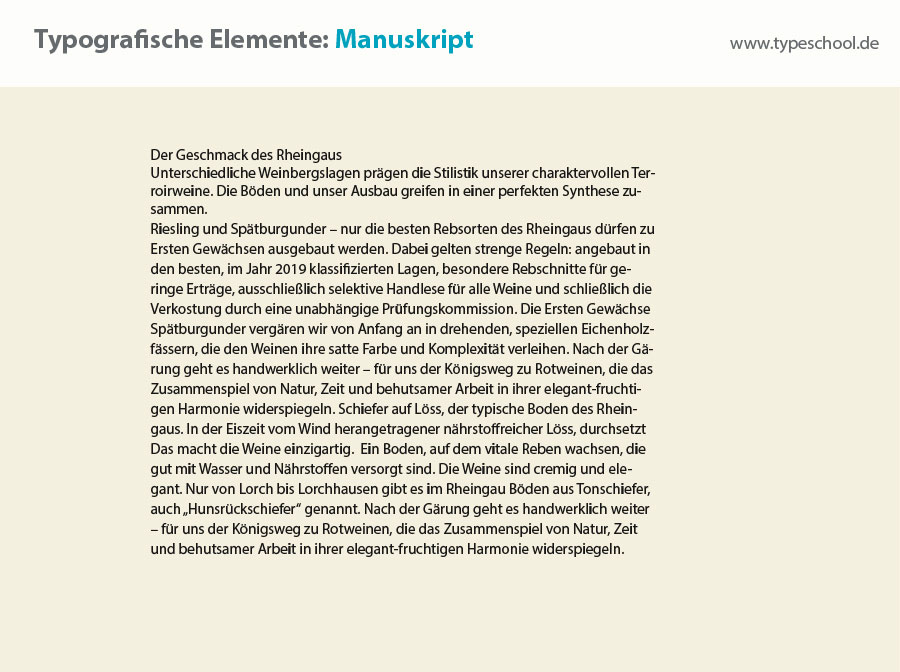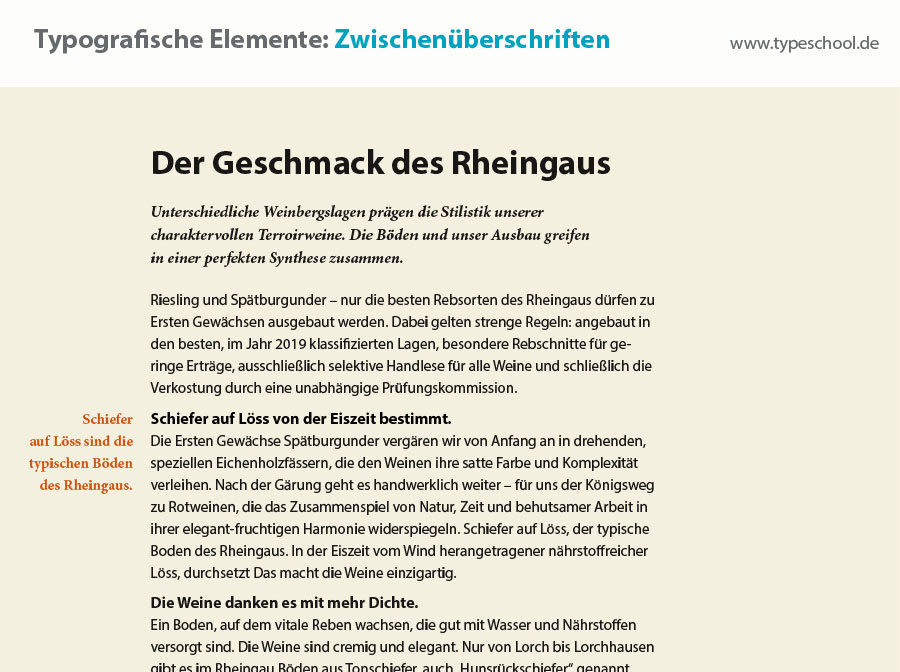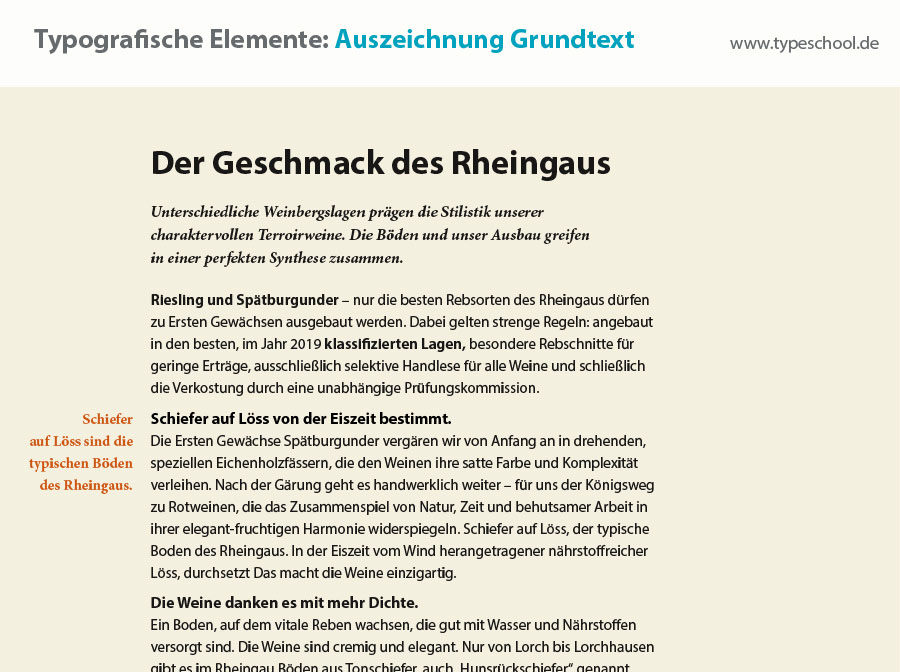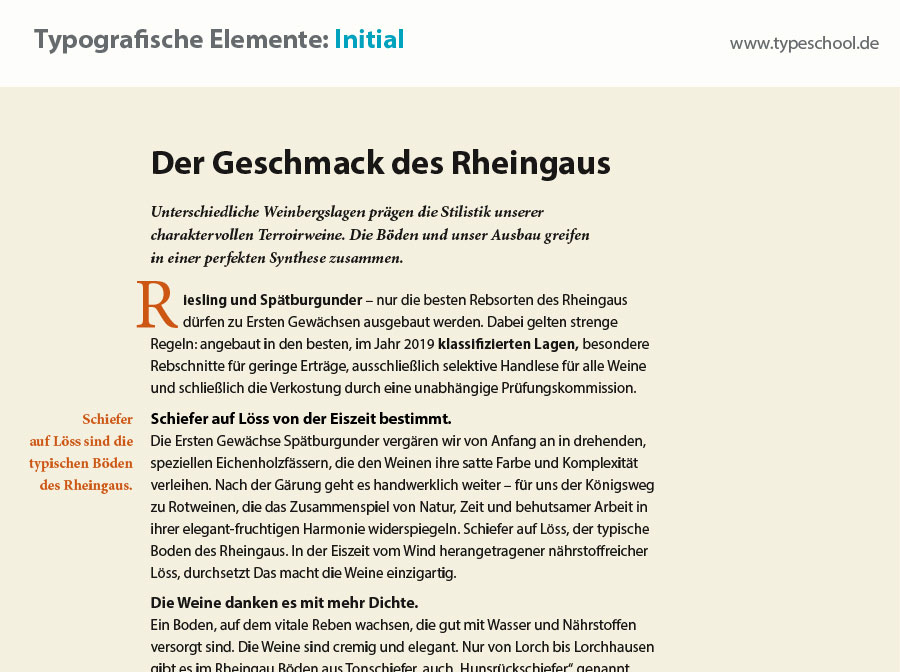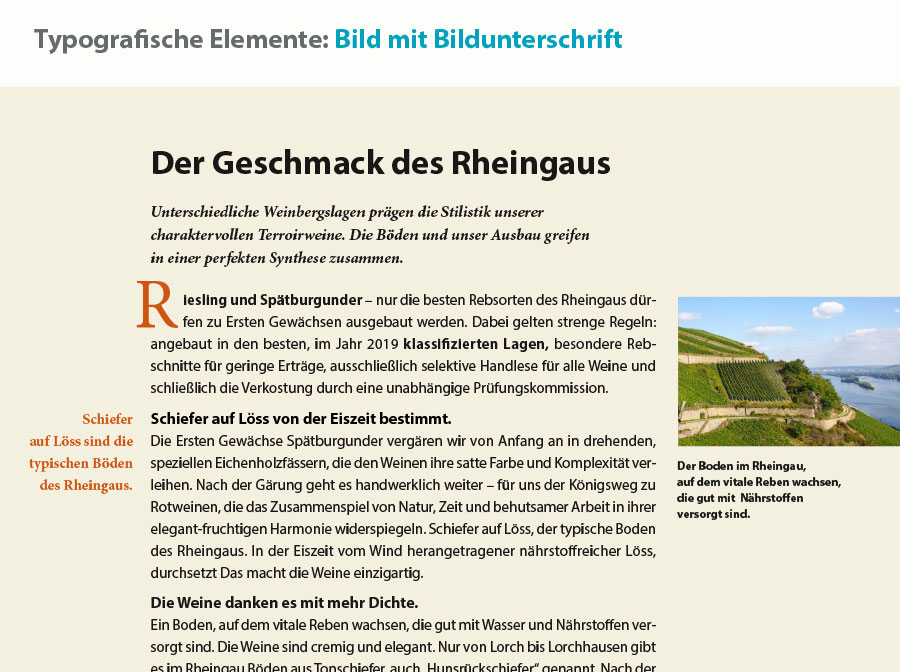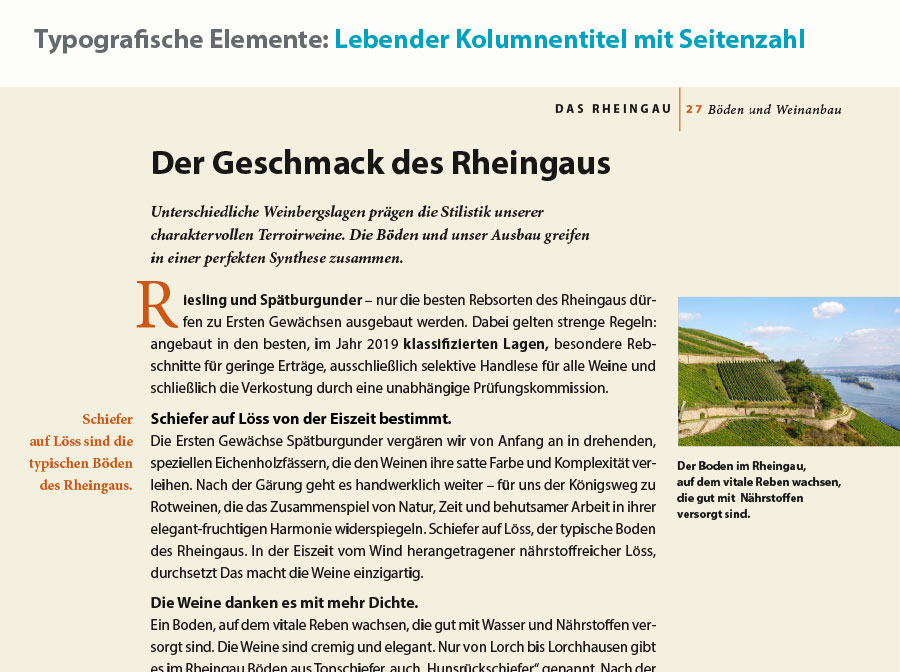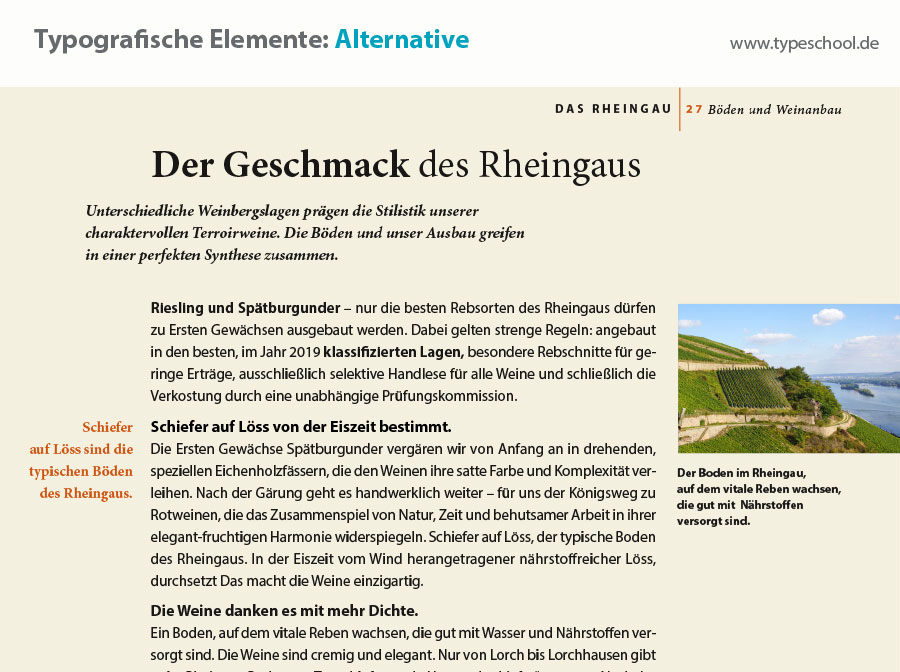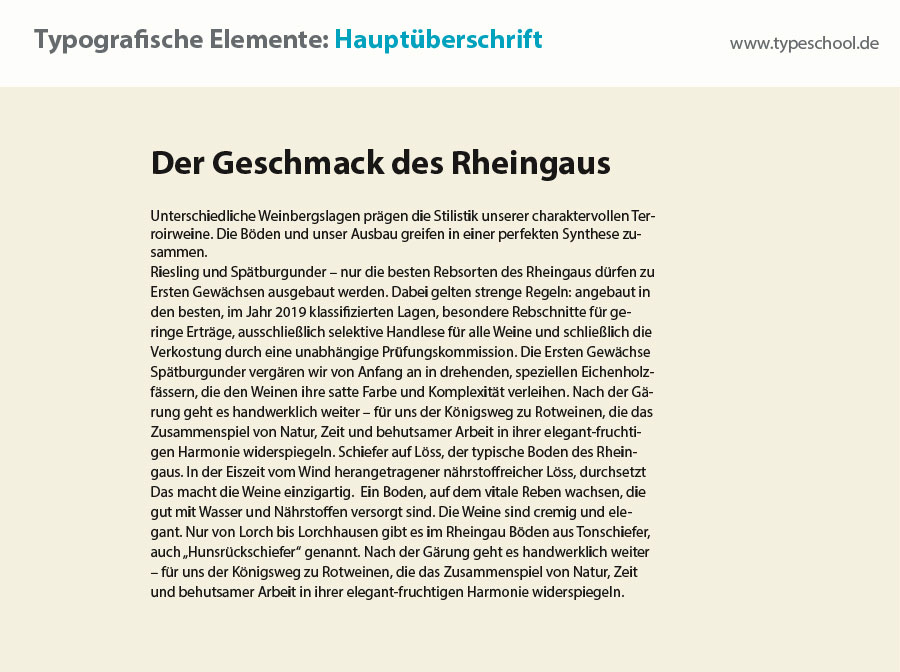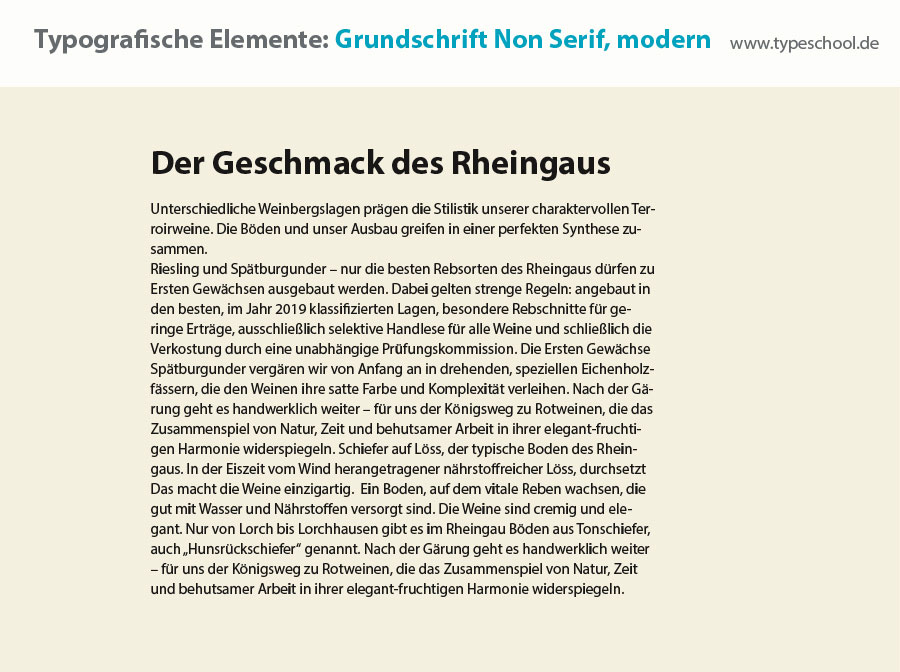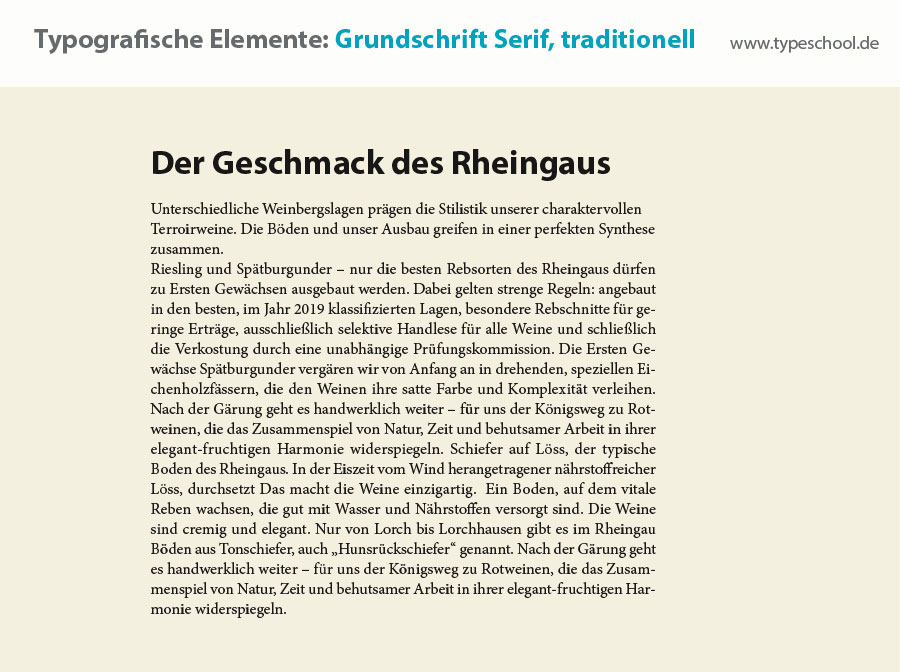
Makro- und Mikrotypografie: mit den wichtigsten typografischen Elementen strukturiert visualisieren – eine Übersicht.
Befragt man Google, was genau man unter Typografie versteht, so erhält man unzählige Antworten und Meinungen. Wikipedia zumindest antwortet eher nüchtern aber sachlich: „Heute bezeichnet Typografie meist den medienunabhängigen Gestaltungsprozess, der mittels Schrift, Bildern, Linien, Flächen und Leerräumen alle Arten von Kommunikationsmedien gestaltet.“ Und weiter: „Mithilfe von Typografie können der Inhalt, der Zweck oder die Anmutung einer Information verdeutlicht werden.“ Quelle: Wikipedia, Typografie.
Typografie ist keine Kunst
Entgegen der Meinung, Typografie sei eine Kunst, die sich auf schöne Schriften, Laufweiten der Schrift oder genauen Zeilenabständen beschränke, halte ich es mehr mit dem Zitat von Günter Gerhard Lange, der einmal sagte: „Typografie übersetzt eine Information in eine Botschaft.“
Ich möchte sogar noch einen Schritt weitergehen: Typografie umfasst visuelle Elemente, mit denen Produkt- oder Dienstleistungsmerkmale transparenter und aufmerksamkeitsstärker dargestellt werden können.
Typografie ist also keine Kunst, sondern einfach gesagt ein Teil der Informations- und Verkaufsförderung. So habe ich es als Typograf, Designer und Inhaber einer Werbeagentur jahrzehntelang gesehen und praktiziert – mit Erfolg!
Typografische Elemente strukturieren Informationen
Was macht Typografie so spannend? Bereits die Auswahl geeigneter Fonts ist der erste wichtige Einstieg in ein neues Projekt – kann man doch damit am besten den Look & Feel eines Designs bestimmen. Auch für einen erfahrenen Designer ist das Thema Schriftauswahl und Schriftmischung immer auch der schwierigste Part im Designbereich. In einem früheren Blogbeitrag habe ich dazu eine Empfehlung gegeben, die Einsteigern und weniger erfahrenen Gestaltern eine Hilfestellung bei der Auswahl von Fonts geben kann.
An dieser Stelle möchte ich Ihnen eine Übersicht geben, welche wichtigen Elemente wir in der Makro- und Mikrotypografie kennen, mit denen wir in Kombination den sogenannten typografischen Spannungsbogen im Layout erzeugen und sich Informationen strukturierter und betonter visualisieren lassen.
Hier ein Ablauf der einfachsten typografischen Elemente, mit denen ich am häufigsten Informationen typografisch strukturiere.
Hauptüberschrift
Die Hauptüberschrift ist der direkte Einstieg ins Thema. Sie strukturiert die Kommunikation und übernimmt auch eine ästhetische Funktion. Die Hauptüberschrift beeinflußt das typografische Klima einer Kommunikation und bestimmt durch die passende Wahl eines Fonts sehr deutlich den Look & Feel eines Designs. Die Hauptüberschrift soll nicht nur informieren, sondern vor allem eine Botschaft transportieren. Gestalterisch hebt sie sich in Schriftgröße und Auswahl der Schrift deutlich vom Grundtext ab.
Grundschrift
Bei der Grundschrift ist die Auswahl der Schriftart sowie die Schriftgröße und der Zeilenabstand besonders wichtig.
Legen Sie fest, ob der Look & Feel eines Designs eher von einer Schrift mit Serifen (Serif Font) oder einer serifenlosen Schrift (Non Serif Font) bestimmt werden soll.
Eine serifenlose Schrift verkörpert eher das Moderne, eine Schrift mit Serifen eher ein gediegenes und traditionelles Design.
Bei Verwendung einer serifenlosen Grundschrift sind Schriftgrößen zwischen 8 und 9 Punkt grundsätzlich geeignet. Eine Grundschrift mit Serifen darf eher einen Punkt größer sein.
Als Zeilenabstand empfehle ich eine Größe von 140 % der Schriftgröße. Ein Beispiel: Beim »Non Serif Font“ Myriad Pro 9 pt wäre für den Lesetext ein Zeilenabstand von 13 pt gut gewählt. Das entspricht auch der heutigen Lesegewohnheit, die durch das Lesen von Texten auf mobilen Endgeräten bestimmt wird. Bei „Serif Fonts“ geben Sie ruhig noch 1 pt dazu.
Bestimmt werden Schriftgröße und Zeilenabstand natürlich von der Schriftart, der Textmenge und der Zeilenlänge – daher vergleichend ausprobieren.
Textvorspann
Der Textvorspann ist ein Bindeglied zwischen Headline und Lesetext. Er soll die erste Aufmerksamkeit aufgreifen und „weiterreichen.“ Im Textvorspann soll inhaltlich alles kommuniziert werden, was der Grundtext vertieft. Gestalterisch soll er sich – wie das Beispiel zeigt –, deutlich in Schriftart, Schriftauszeichnung, Schriftgröße, Zeilenlänge, Zeilenabstand und Satzart von der Hauptüberschrift und dem Grundtext unterscheiden.
Marginaltext
Marginalien sind Randbemerkungen, die zusätzliche Informationen oder weitergehende Erklärungen zum Grundtext bieten. Marginalien sind seit dem Mittelalter als handgeschriebene Randspaltentexte bekannt, die handschriftlich in den Kodex oder die Inkunabel eingetragen wurden.
Wir verwenden sie heute in Ratgeberreihen, Fachmagazinen oder Reiseführern sehr häufig, um wichtige Textinhalte zusammenfassend oder einleitend zu betonen. Dabei werden Marginal-Infos immer am linken oder rechten Textrand positioniert, um diese hervorzuheben.